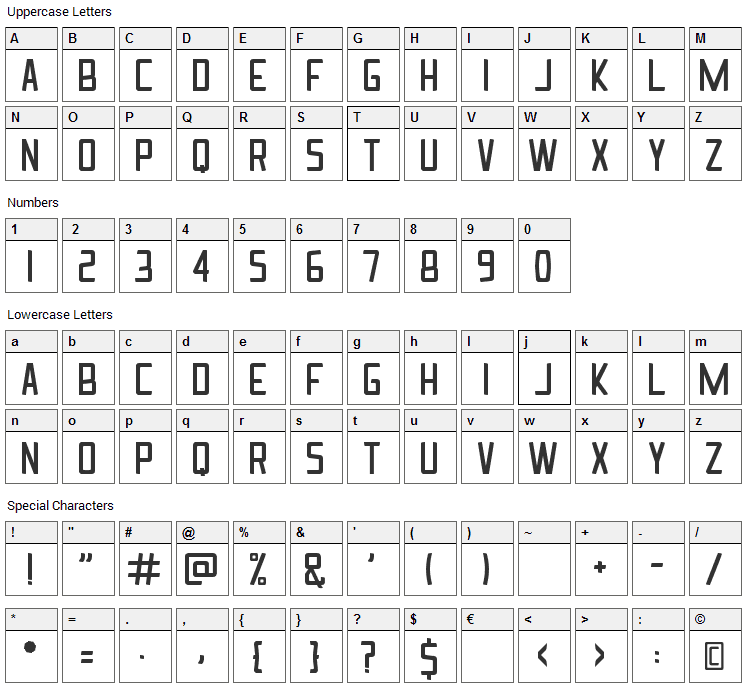
Ingrata Font
Font Name:Ingrata
Developer:EH Martuchelli
• Designer:Elvis H. Martuchelli @ a Falange | est?dio
Set tipogr?fico criado para a conclus?o de semestre da disciplina de Tipografia da Universidade Anhembi Morumbi. Fonte elaborada sob a orinta?nao do Prof. Tadeu Costa ? quem somos muito gratos pela paci?ncia. S?o Paulo - Brasil - 2005/2.